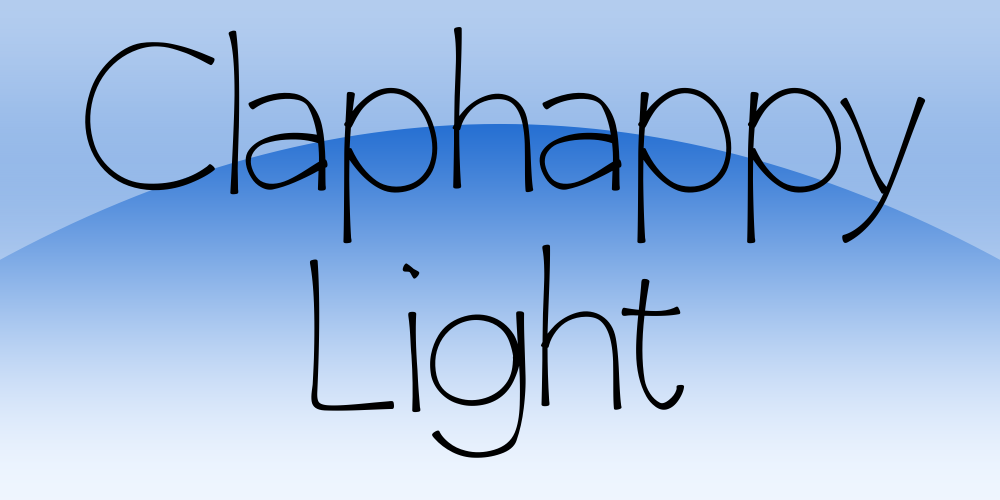
Claphappy Light font – Download Grátis
A Claphappy Light é uma nova adição à família de fontes Script do mundo dos criativos digitais brasileiros. Inspirada no estilo elegante dos anos 1920, esta fonte traz um toque de charme e sofisticação aos projetos, fazendo dela a escolha ideal para letras de emails ou design gráfico delicado. Desenvolvida pelo designer Hamilton em colaboração com equipes de designers digitais brasileiros, ela é perfeitamente adaptada para criar mensagens de email encantadoras ou designs gráficos minimalistas e sofisticados. A Claphappy Light não apenas adiciona uma dimensão visual a qualquer projeto, mas também oferece um charme único que se torna facilmente reconhecível em qualquer mídia digital. Seu design elegante combina harmoniosamente com diversos estilos de projetos, incluindo design gráfico minimalista, e-mail personalizado e até mesmo ilustrações. A Claphappy Light é uma opção sólida para designers que valorizam os detalhes e gostam de criar experiências visuais únicas em suas criações digitais. Sem dúvida, a fonte Claphappy Light é um excelente exemplo da criatividade brasileira na fabricação de fontes, oferecendo aos designers uma ferramenta adorável para explorar seus projetos em novas e encantadoras direções visuais.